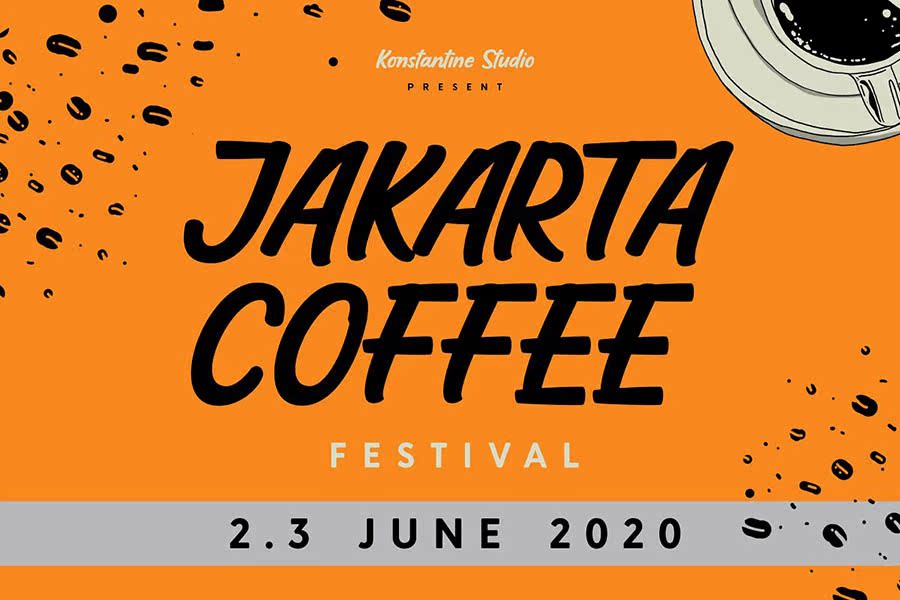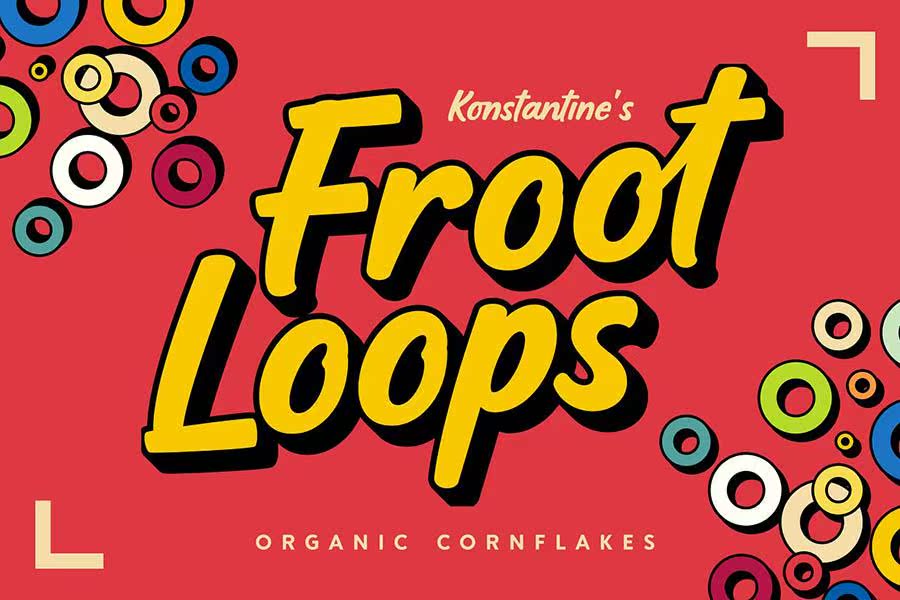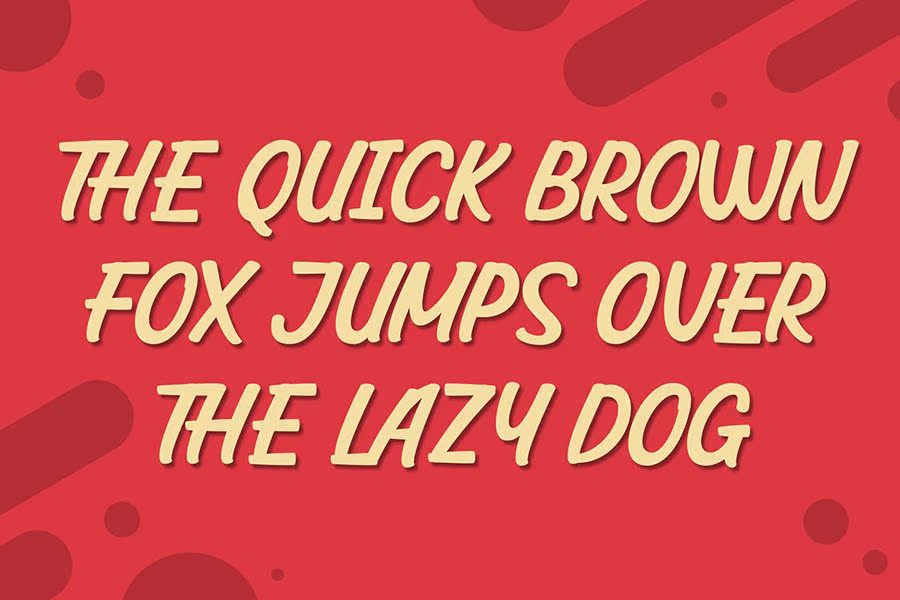
SayHellotoHoffersPlayfulDisplayFont!ABOLD和CASUALSCRIPT字体,带有营销和写作氛围的实现。有些是连接的,而另一些则不是。非常适合CASUALCOTYPE、Food和Beveragebranding、书籍封面,任何时候都需要有趣的故事,Hoffersistheanswer。